Schriftklassifikation Matrix Beinert
Die »Matrix Beinert« ist Schriftklassifikationsmodell für das Electronic und Desktop Publishing (DTP), welches 2001 vom deutschen Typografen Wolfgang Beinert erarbeitet und zuletzt im Dezember 2025 aktualisiert wurde. Das Schema ordnet Druckschriften, Screen Fonts, Webfonts und Bildzeichen in neun Hauptgruppen:
1. Antiqua
2. Egyptienne
3. Grotesk
4. Zierschriften
5. Screen Fonts
6. Corporate Fonts
7. Gebrochene Schriften
8. Nichtrömische Schriften
9. Bildzeichen
Die Schriftklassifikation nach der Matrix Matrix dient dem Katalogisieren, dem Ordnen, der Pflege und der Verwaltung von Fonts in Schriftsammlungen (Schriftenbibliotheken) auf Computern 1) bzw. dem Studium von digitalen Schriften und deren Klassifikation.
Die Matrix Beinert wurde – im Gegensatz zu der deutschen »DIN 16518« für materielle Druckschriften im Bleisatz – insbesondere für den digitalen typografischen Workflow in professionellen Corporate Publishing Unternehmen für die Medien-, Wirtschafts- und Unternehmenskommunikation konzipiert, beispielsweise für Verlage, Designbüros oder Kommunikationsagenturen. Deshalb berücksichtigt die Matrix bereits auf der ersten Hierarchieebene (Hauptgruppen) Screen Fonts, Corporate Fonts und Bildzeichen.
Sinn und Zweck ist die Optimierung typografischer Gestaltungs- und Arbeitsprozesse, beispielsweise die gezielte Auswahl von Schriften, optimiertes Zeit- und Qualitätsmanagement, juristische und technische Produktionssicherheit sowie weniger Opportunitätskosten.
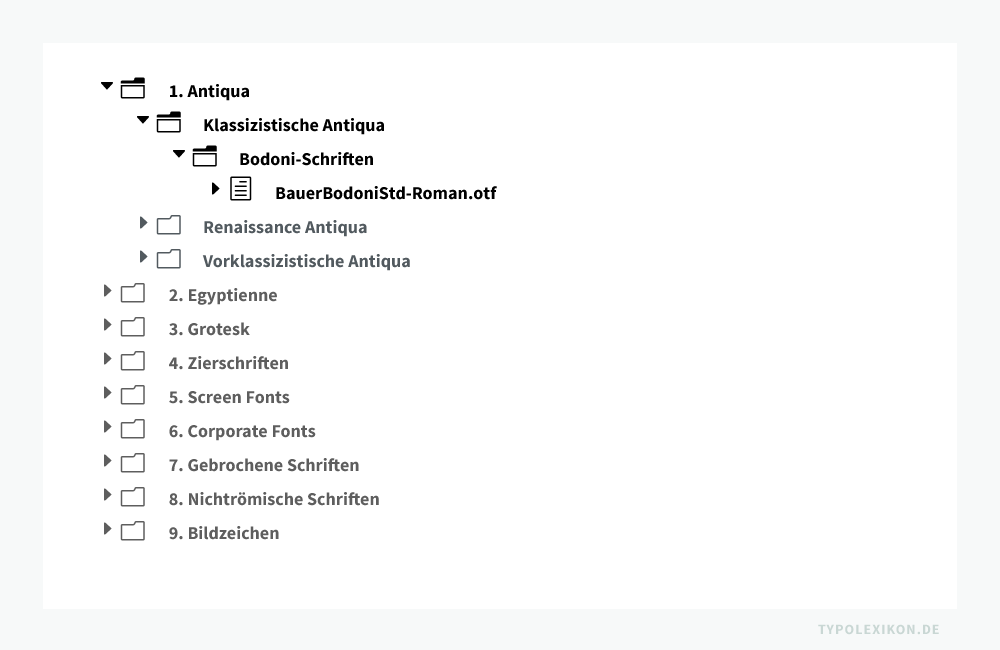
Durch diese Neugruppierung ist es nun auch für einen User mit geringen typografischen Kenntnissen möglich, Druckschriften und Screen Fonts, zumindest auf der obersten Hierarchieebene, plattformunabhängig auf jedem Microcomputer zeitgemäß zu ordnen, was mit anderen Klassifikationsmodellen, beispielsweise Vox, Thibaudeau, Novarese, Alessandrini-Codex, British Standard oder DIN 16518, nicht möglich ist.
Problematik Druckschriften, Screen Fonts und Webfonts
Die Gewichtung der Matrix Beinert liegt weiterhin auf der Klassifikation von Druckschriften, da die Darstellungsqualität von Screen Fonts (z.B. TTF Desktop Fonts oder Webfonts, z.B. woff2) im Vergleich zu im gewerblichen Hauptdruckverfahren nach DIN 16500 2) gedruckten PostScript®-Schriften (z.B. OTF Fonts) noch immer spürbare, teils gravierende Defizite aufweisen. Insbesondere die exakte Klassifikation von Webfonts in Unter- und Nebengruppen in kleinen Schriftgraden, also in Konsultations- und Lesegrößen, ist auch an hochauflösenden 5K Retina Display Monitoren bis heute noch nicht oder kaum möglich, selbst wenn diese aus der Typometrie klassischer Druckschriften 1:1 abgeleitet wurden. Linear interpolierbare OpenType-Fonts, sogenannte »Variable Fonts«, verstärken die Problematik.
Druckschriften werden also in ihrer gedruckten Form und Screen Fonts am Bildschirm evaluiert. 3) Die Problematik, Print-, Desktop- und Web-Varianten der gleichen Schriftfamilie getrennt zu ordnen, kann jeweils durch eine Shortcut- bzw. Aliasdatei (Dateiverknüpfung) aufgelöst werden.
Typifikation
Die Eingruppierung einer Schrift erfolgt in der Regel nach entsprechend nachvollziehbaren Merkmalen und wird jeweils durch Beispiele veranschaulicht. Des Weiteren entsteht – je nach Anforderung und Kompetenz des Users – im Prinzip eine unbegrenzte Anzahl von individuellen Unter- und Nebengruppen, die sämtlich auf stilistischen Merkmalen fußen. Die Matrix Beinert korrespondiert mit internationalen Standards und Termini.
Beispiel einer philologischen Klassifikation in Form der Matrix Beinert anhand einer Bauer Bodoni Roman von Linotype®:
| Taxonomie | Beispiel | |
|---|---|---|
| Schriftgattung: | Antiqua-Schriften | |
| Hauptschriftgruppe: | Antiqua (Serif) | |
| Schriftuntergruppe (Schriftart): | Klassizistische Antiqua | |
| Schriftnebengruppe: | Bodoni-Varianten | |
| Schriftbezeichnung: | Bauer Bodoni™ | |
| Schriftschnitt | Roman | |
| Schriftgestaltung Original: | Giambattista Bodoni | |
| Schriftgießerei Orginal: | Stamperia reale, Parma | |
| Schriftgestaltung Remake: | Heinrich Jost und Lois Höll, 1926/1927 | |
| Schriftgießerei Remake: | Bauersche Gießerei | |
| Lizenzgeber: | Bauer Types S.A. | |
| Vertrieb: | Linotype® | |
| Figurenverzeichnis: | W2G, 2013, 420 Characters | |
| Tastaturcodierung: | Unicode | |
| Technologie: | OpenType, CFF, PostScript® 1 | |
| File Name: | BauerBodoniStd-Roman.otf | |
| Windows® Menüname: | Bauer Bodoni Std | |
| PostScript® Name: | BauerBodoniStd-Roman | |
| Langer PostScript® Name: | BauerBodoniStd-Roman | |
| Katalognummer: | 16740074 | |
| Stand: | 1.2015 | |
Haupt- und Untergruppen der Matrix Beinert 4)
1. Antiqua
Rundbogige Antiqua-Druckschriften römischen Ursprungs mit Serifen (Serif)
-
- Klassizistische Antiqua
- Renaissance-Antiqua
- Französische Renaissance-Antiqua
- Venezianische Renaissance-Antiqua
- Vorklassizistische Antiqua
2. Egyptienne
Rundbogige Antiqua-Druckschriften römischen Ursprungs mit betonten Serifen (Slab Serif)
-
- Clarendon
- Egyptienne
- Egyptienne Varianten
- Italienne
- Schreibmaschine
| ↑3 | Anmerkung: Unabhängig von der Typometrie und des Hintings eines Webfonts, weicht die Darstellung auf unterschiedlichen Ausgabegeräten grundlegend je nach verwendeter Hardware, Betriebssystem, Browser, Browserversion, Grundeinstellungen des Browsers, Bildschirmqualität, Bildschirmauflösung, Anti-Aliasing, Grafikkarte, etc. spürbar voneinander ab. |
| ↑4 | Anmerkung: Die Untergruppen sind alphabetisch geordnet. |
| ↑5 | Anmerkung: Bezeichnungen und Anzahl der Unter- und Nebengruppen ergeben sich nach individuellen Anforderungen. |